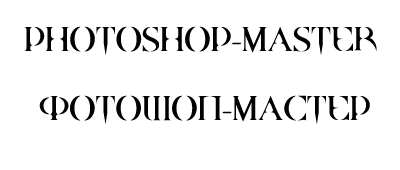
Обожаю игру)) и шрифт тож ниче)
"дорогая прстота" -красивый шрифт,спасибо
Крутоооо)
прикольно
Квака жива!
Da лан тебе, и ща неплохо)
мда... лет так 7 назад он бы пользовался спросом (как "СТАЛКЕР" сейчас).... а так старо.... старо.